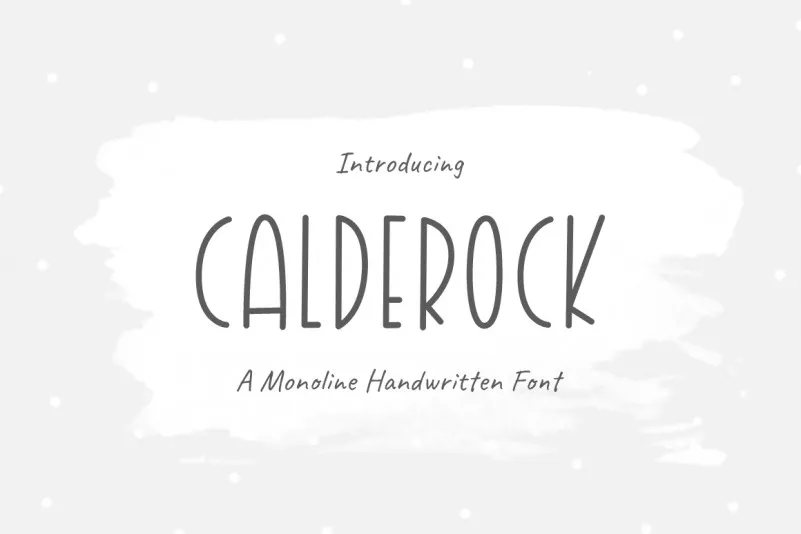
Calderock Font – Download Grátis
Esta font ‘Calderock’ é perfeita para quem busca uma leitura clara e elegante ao mesmo tempo. Ela tem o formato de linhas monolineas, oferecendo letras altas e escuras que permitem que qualquer texto seja lido com facilidade. Suas características fazem-a uma escolha ótima tanto para citações quanto para estilos de marca, aplicações em t-shirts, sites, blogs ou até mesmo para criação de logotipos. Este design de fonte é versátil o bastante para atender a diversos tipos de projetos – seja um design infantil leve e colorido ou uma aplicação profissional sofisticada. Seja qual for seu projeto, ‘Calderock’ tem tudo o que você precisa para tornar suas criações ainda mais únicas e memoráveis.
Designer: jimtypestudio